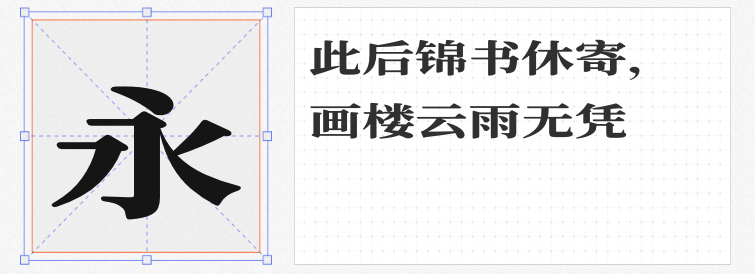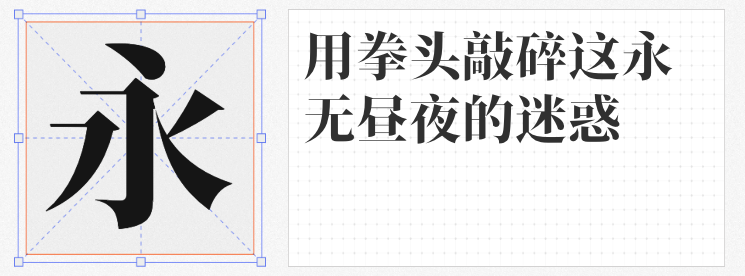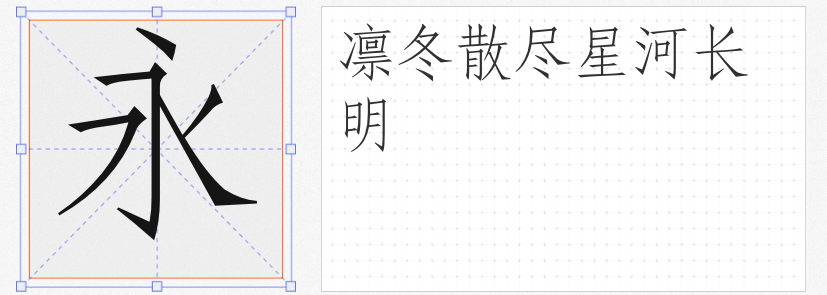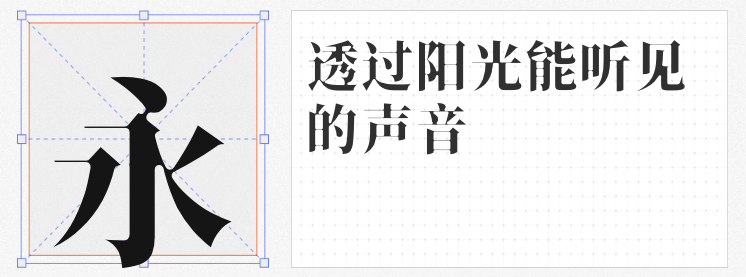
宋体作为汉字设计的经典范式,历经千年演变,始终以“横细竖粗”的骨骼与“三角饰角”的韵味,承载着东方美学的基因。在数字时代,免费商用宋体不仅延续了这一文化脉络,更通过创新设计适配多元场景。本文精选四款风格各异的免费宋体,从温润现代到刚柔并济,为设计师提供兼具实用性与艺术性的字体解决方案。
基于思源宋体优化的寒蝉锦书宋,通过圆角处理与字重重构,将传统宋体的锐利感转化为柔和气质。其「Wide ExtraBold」宽体版本横向拓展笔画宽度,形成如碑刻拓印般的厚重感,却因圆角设计保留了呼吸空间。字体粗细比例经过精密调整,即使在小字号下仍能保持清晰可读性,适合文化类海报标题、品牌标语等需要传递稳重感又不失亲和力的场景。
香萃潮汐宋以「蛛网浓雾」为灵感,将笔画折角转化为圆角,并通过粘连设计营造藕断丝连的朦胧感。W40字重通过横细竖粗的极致对比,形成如潮汐般柔中带刚的视觉节奏。其线条光滑且富有曲线韵律,既适用于书刊封面传递古典雅韵,也可用于恐怖题材海报制造心理压迫感,甚至在时尚品牌广告中,能以矛盾美感诠释先锋态度。
这款字体复刻了宋版书刻本的工整风骨,将楷书的笔意融入宋体结构,形成笔画粗细均匀、字身修长的独特风格。其横斜竖直、起落偏顿的笔画特征,既保留了欧柳书法的严谨韵律,又通过均匀的间隔与挺拔的出锋,适配现代屏显阅读需求。无论是古籍数字化排版、传统茶饮包装,还是需要传递文化厚重感的品牌视觉系统,均能游刃有余。
作为思源宋体的改造体,新愚公装甲宋A试图在宋体骨架中注入装甲的硬核质感。通过笔画切割与倾斜处理,部分字符呈现出断笔的工业感,而未断笔处则保留了宋体的传统韵味。尽管存在断笔夸张的争议,但其超粗字重仍可应用于科技产品海报、运动品牌宣传等需要冲突感的场景,以机械与人文的碰撞传递力量美学。